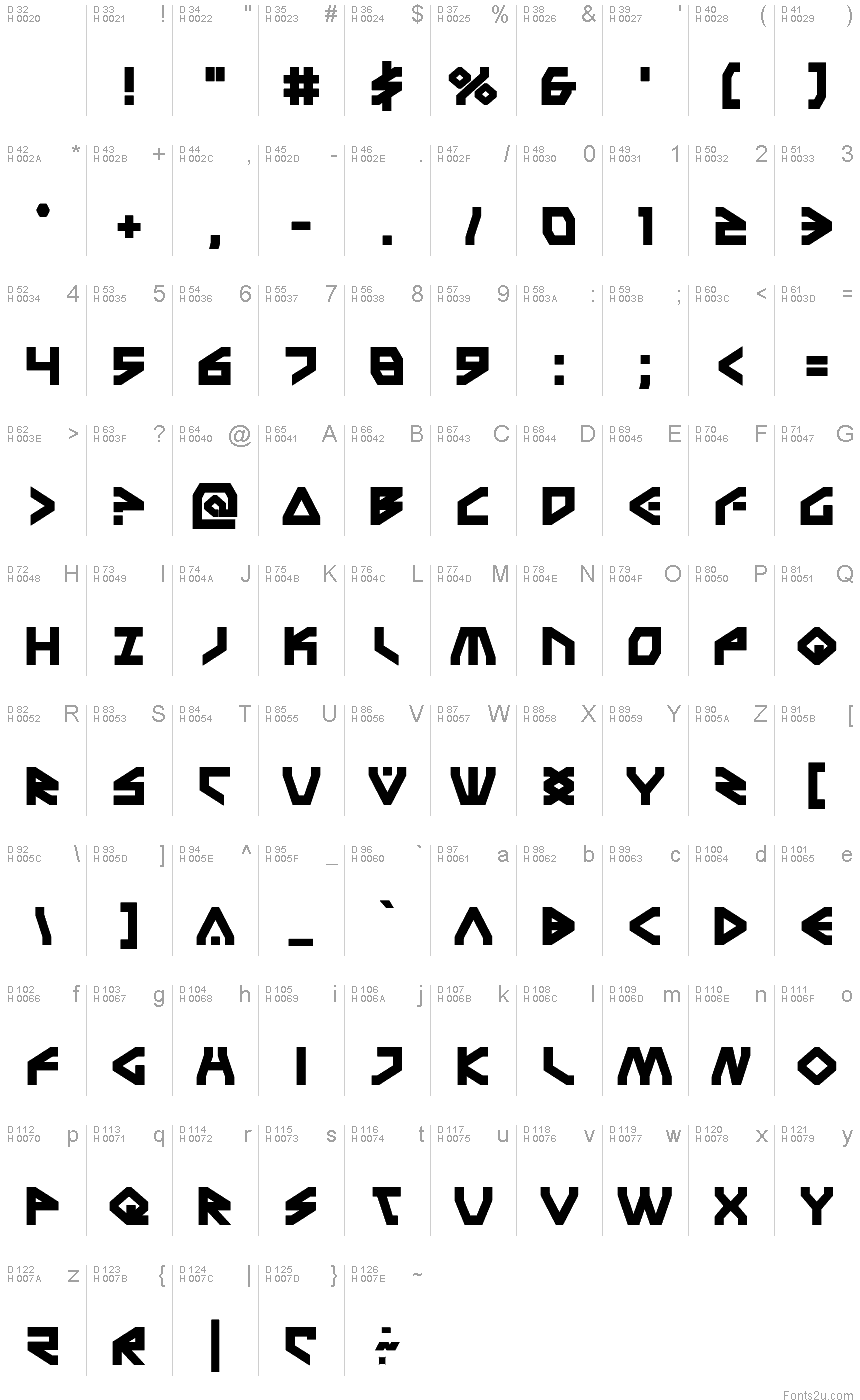
Terra Firma Bold
Terra Firma Bold von Iconian Fonts ist eine kostenlose, kantige Techno-Display-Schrift mit einem scharfkantigen, futuristischen Charakter. Die Buchstaben basieren auf scharfen Schnitten und breiten diagonalen Verbindungen, was der Schrift eine gemeißelte, konstruierte Anmutung verleiht, die eher an Sci-Fi-Insignien erinnert als an neutrale Geometrie.
Sie passt hervorragend zu Game-Logos, E-Sport-Branding, Plakatüberschriften, Album-Covern und Titelkarten für Motion Graphics, wo kurze Wörter ihre aggressive Silhouette optimal zur Geltung bringen. Als kostenloser Font eignet sie sich auch perfekt für Monogramme und Cover-Texte, besonders wenn Sie eine Typografie suchen, die kompakt, mechanisch und etwas streng wirkt.